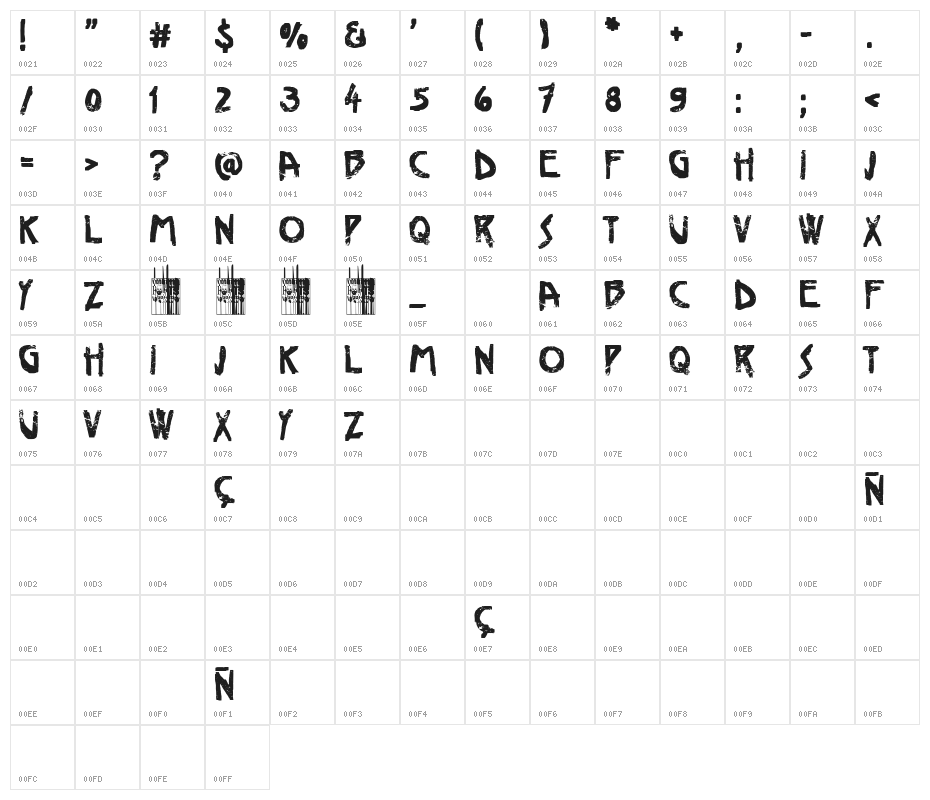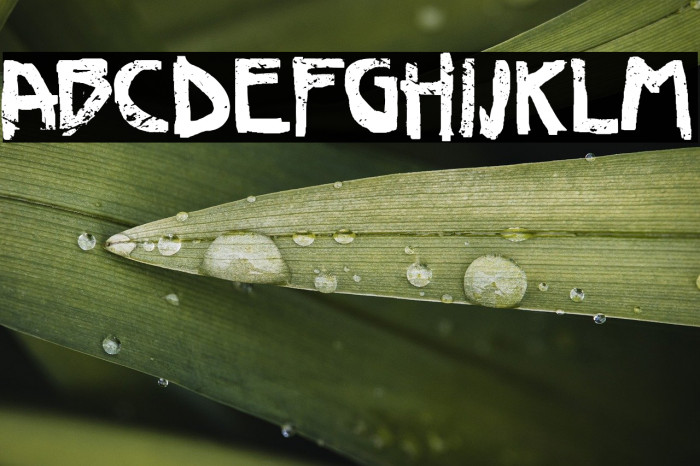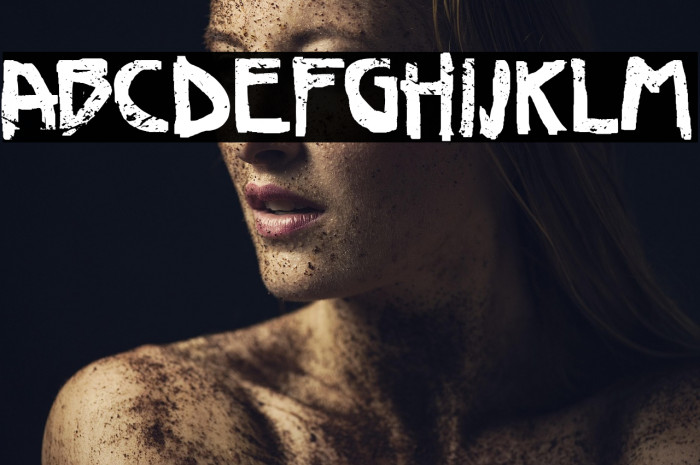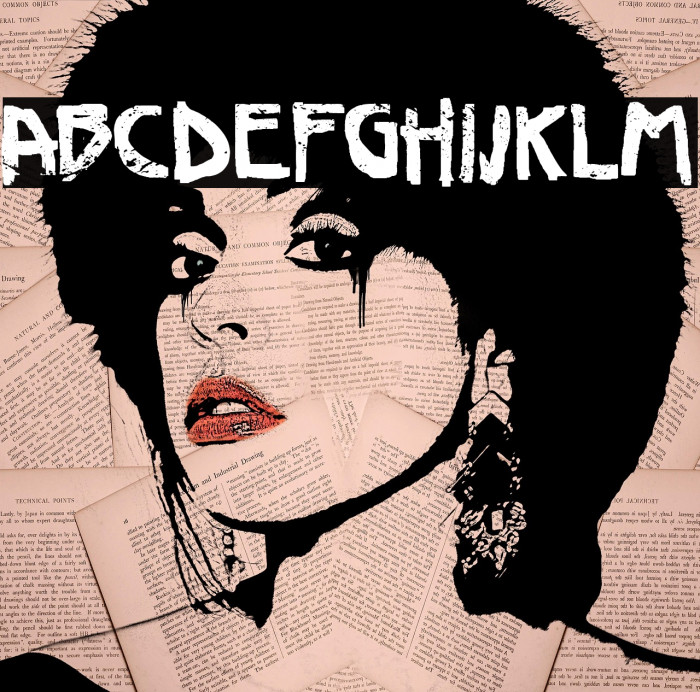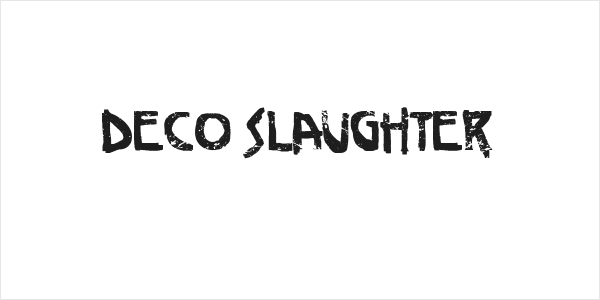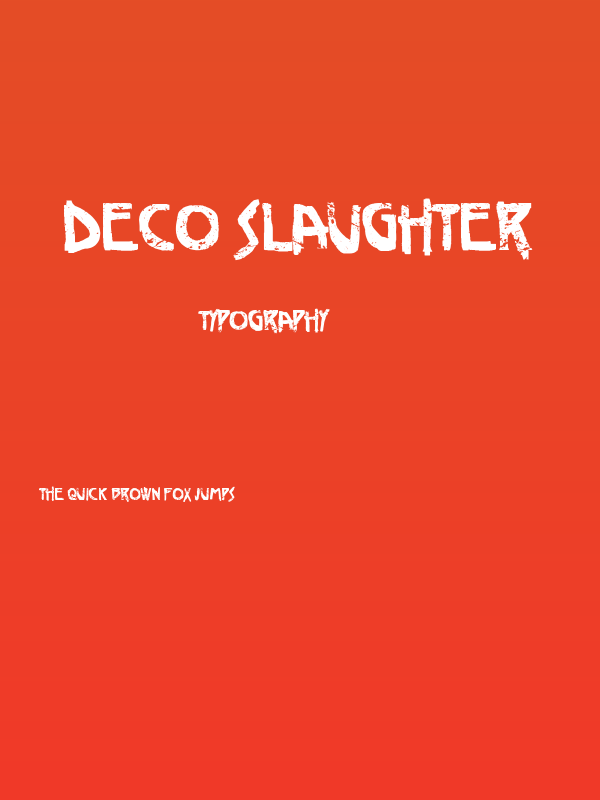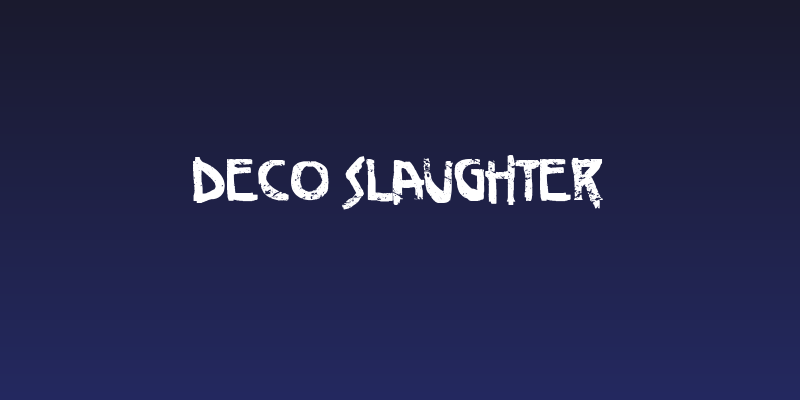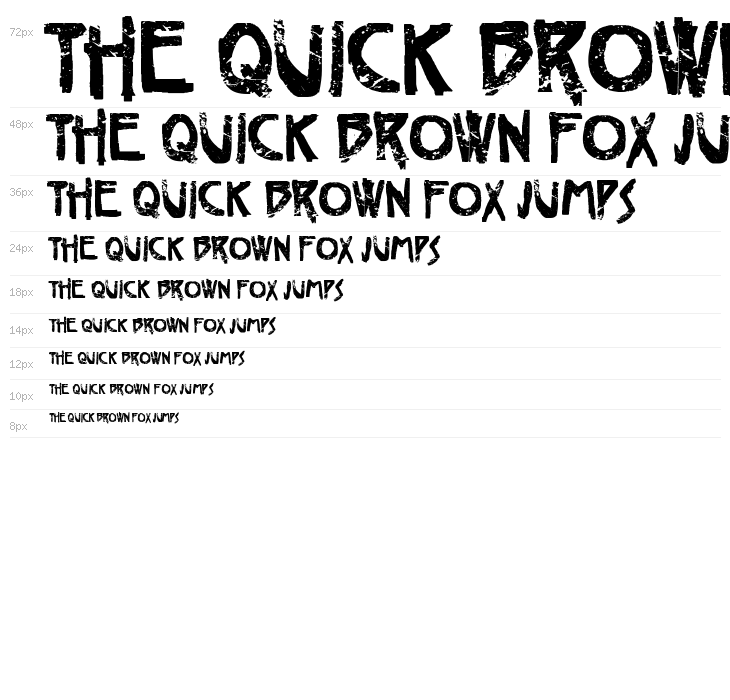
Deco Slaughter Font
✎ Messy
| Progetti proposti | Ideal for projects requiring a bold statement, such as posters, album covers, or branding for edgy or alternative products. |